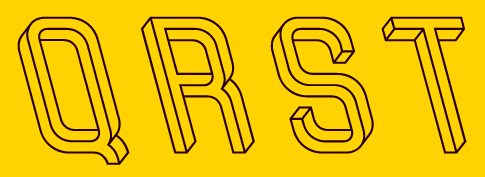
Венгерский дизайнер Марци Хегедус создал оригинальный шрифт Frustro, который основан на идее невозможных фигур - одного из видов оптических иллюзий. Как и классический треугольник Пенроуза, буквы этого шрифта можно представить направленными или в одну, или в другую сторону, и для них невозможно создать 3D-модели.
В своём блоге Марци Хегедус объясняет, каким образом он добился такого эффекта, на примере буквы 'R': он совмещает левую верхнюю часть и правую нижнюю часть двух 3D-моделей, после чего чертит проекцию.